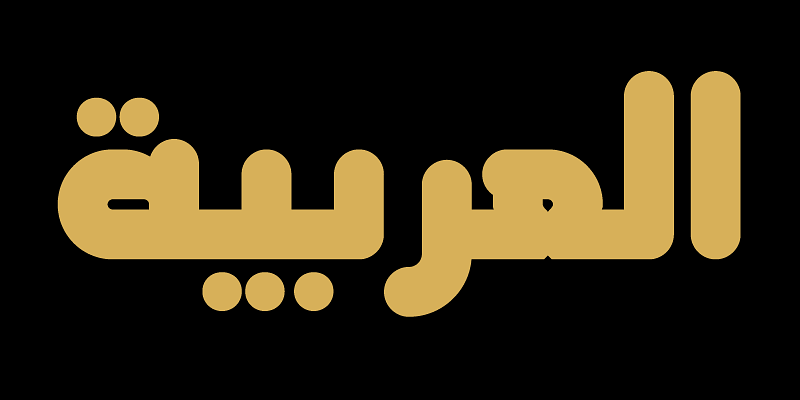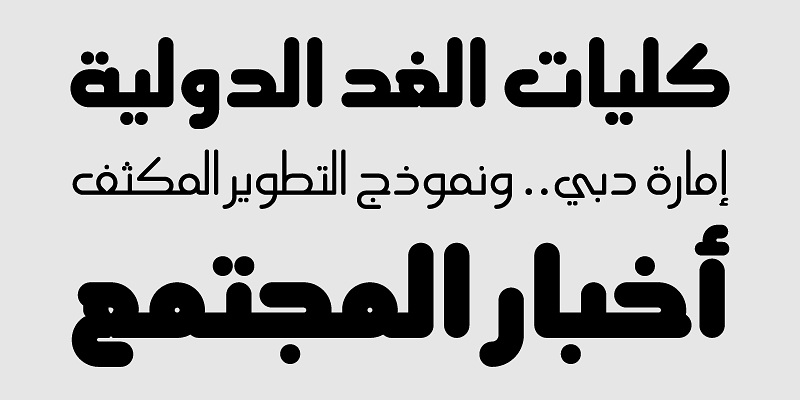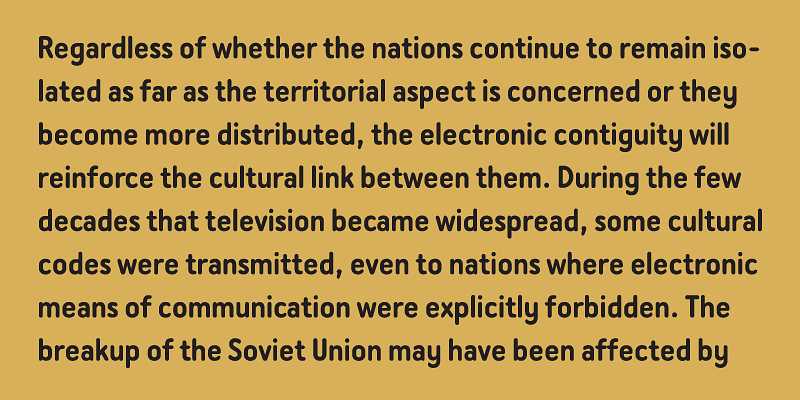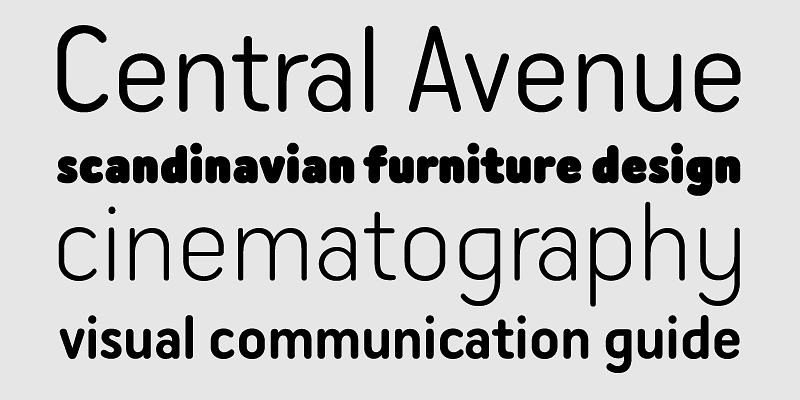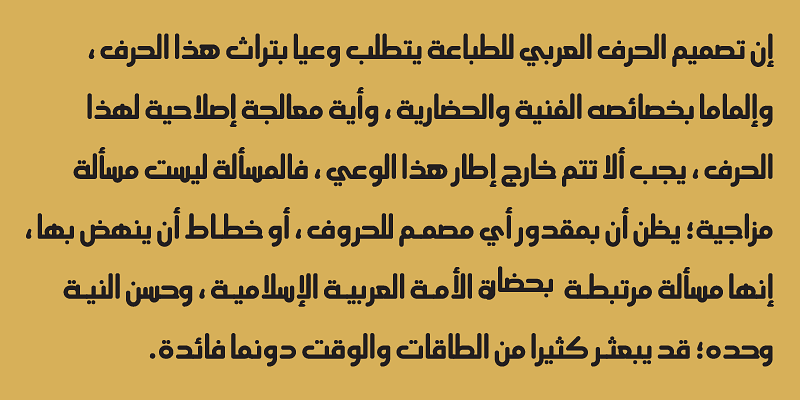
PF Aljamal은 다양한 변주 세트가 있는 현대적인 아랍어 원형 서체이며 사실상 동종 최초라 할 수 있습니다. 부드럽게 둥근 말단부는 굵은 두께에서 강한 인상을 주며, 문서 본문에 작은 크기로 설정하면 미묘하고 친숙한 느낌을 전합니다. 본질적으로 다소 캐주얼하지만 동시에 강력한 기하학적 구조로 인해 탄탄하고 견고합니다.
PF Aljamal은 무게 대비에 균형이 잡혀 있으며 명확하고 단순한 구조 덕분에 작은 크기에서도 가독성이 매우 높습니다. 총 7가지 변주 형태로 구성되어 있어 다양한 응용 분야에서 사용할 수 있습니다. PF Aljamal은 아랍어, 라틴어, 페르시아어, 우르두어 및 쿠르드어를 지원하며 10가지 고급 OpenType 기능을 제공합니다.